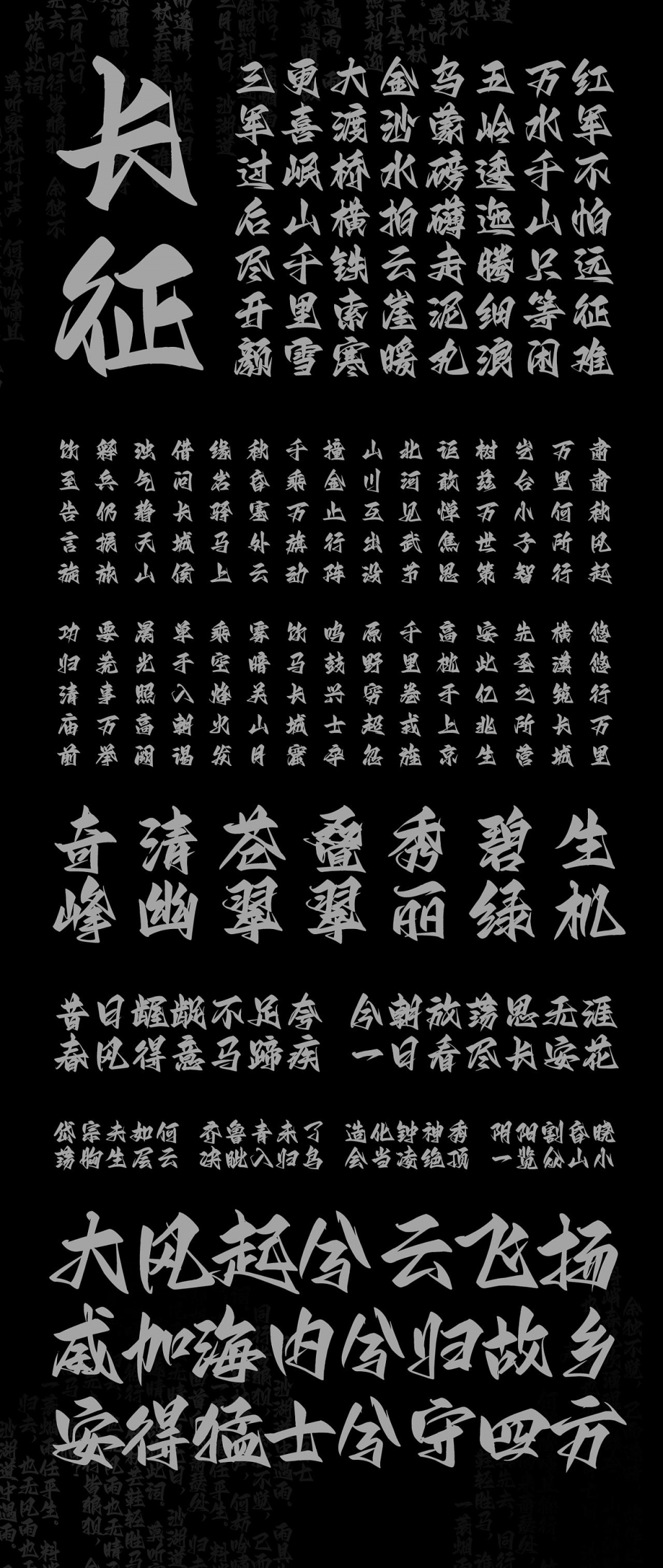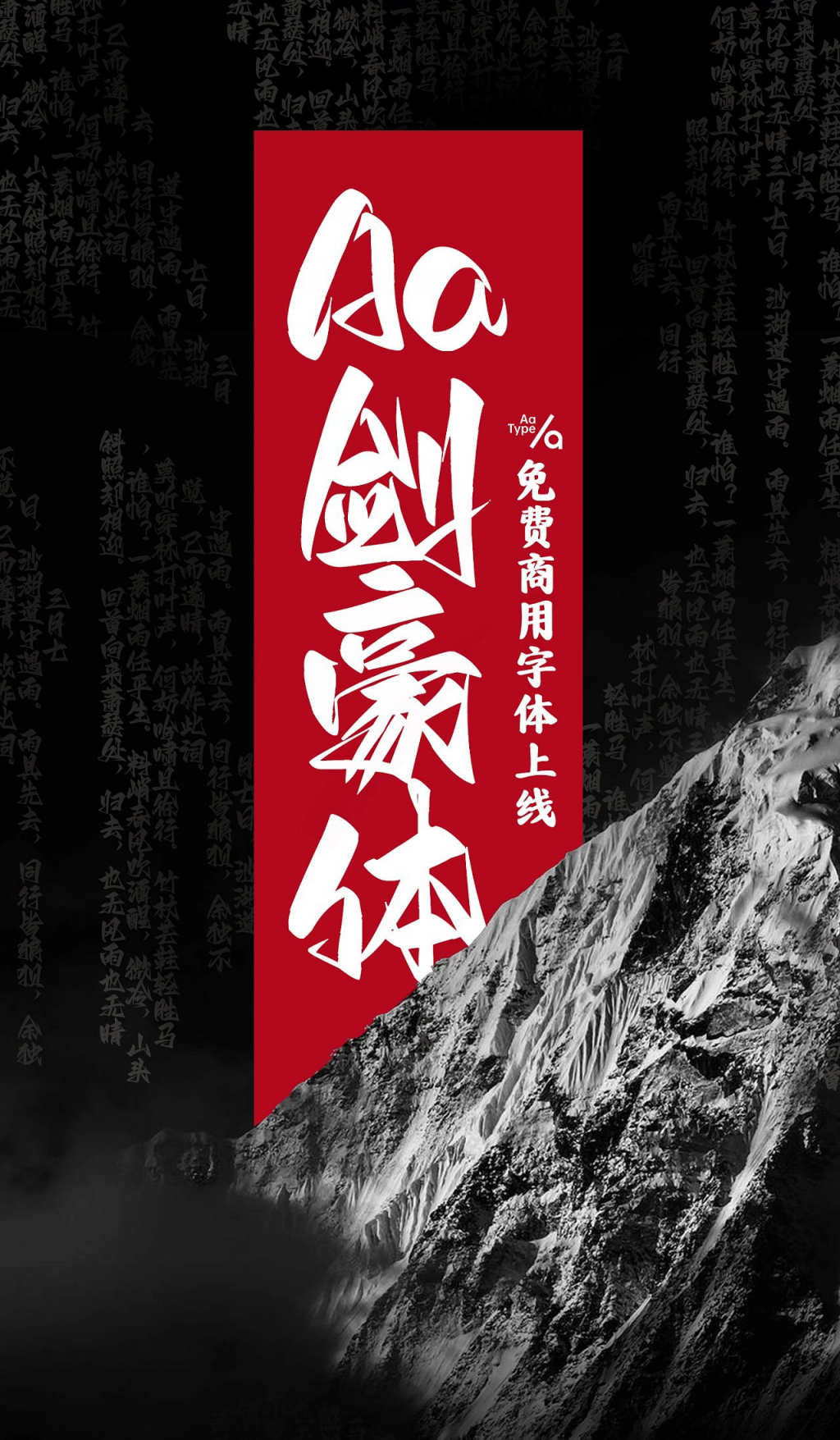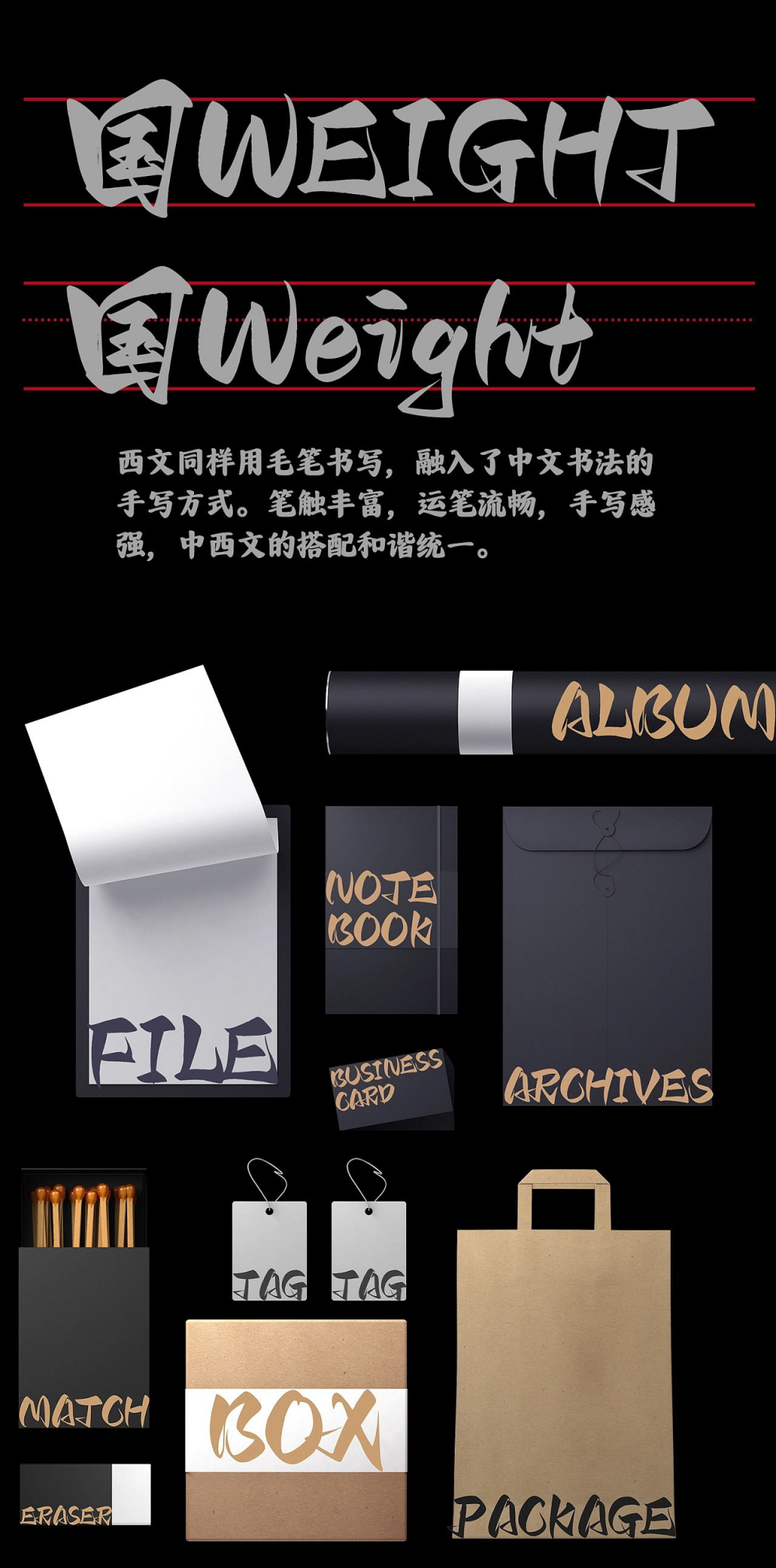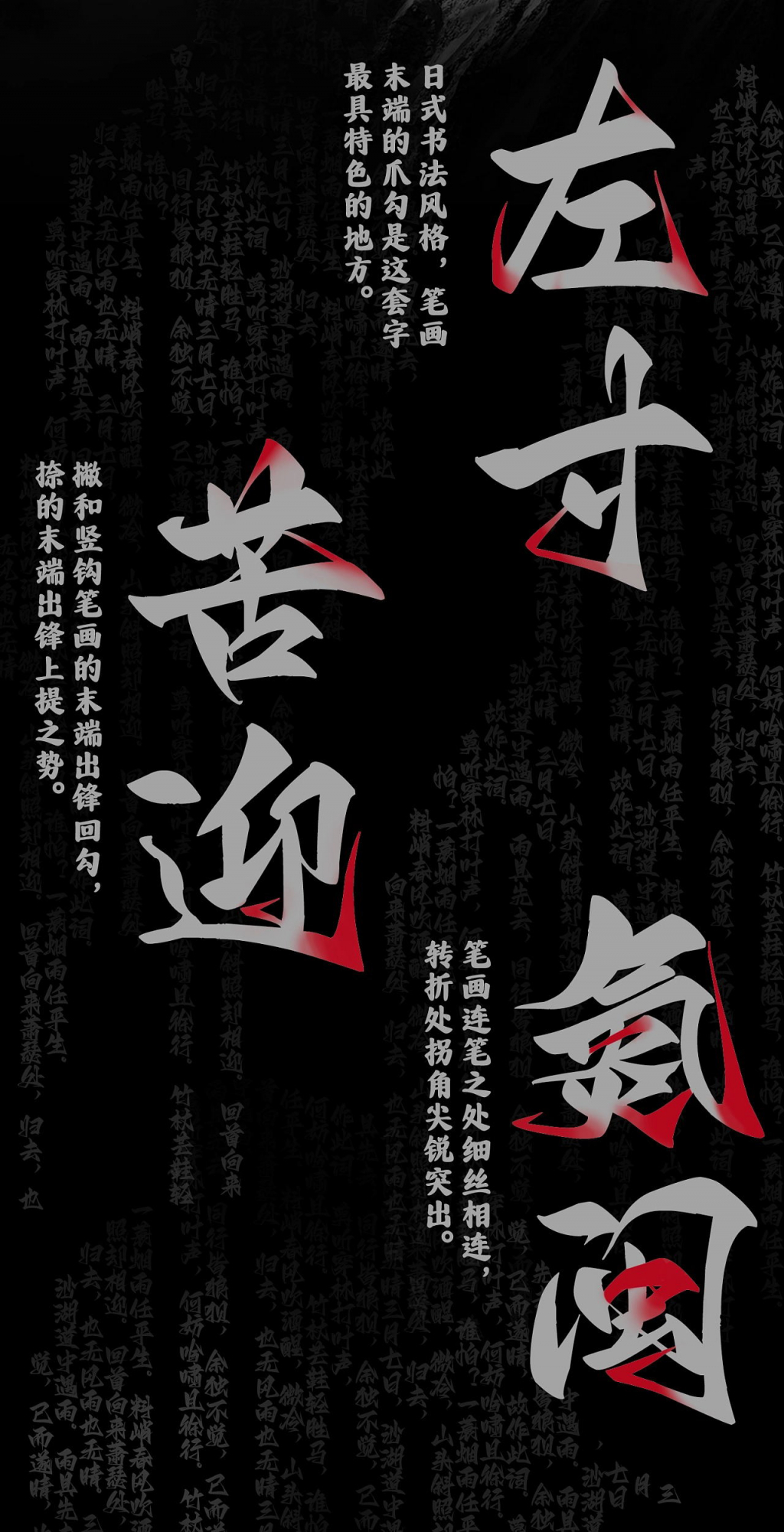
Aa剑豪体Aa字库的首款免费商用字体,这款字体透着一股江湖豪气,一笔一划都衬托着洒脱、豪放,适合应用于艺术设计、平面宣传设计、网页设计,书法字帖等领域。据猫啃君的小道消息,除了Aa剑豪体,Aa字库还有另外一款免费商用字体正在制作中,迟些也会择机发布。
“Aa剑豪体”是一款书写很新颖的字体,字体大方,适合各种设计作品使用!欢迎下载!